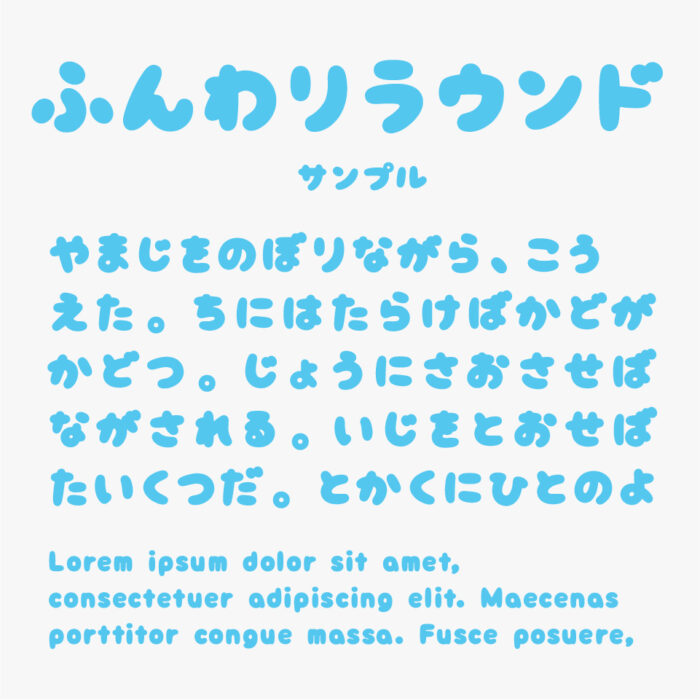
ふんわりラウンド
ふんわりラウンドフォント
ふんわりラウンドフォントは、やや手描き風の骨格で、丸ゴシックのような太めの先端丸の線のベースとしている手書き風フォントです。
ふわふわな雲のような丸みがあり可愛らしいフォントになっているので、子供っぽいデザインとの相性が良いフォントです。
ふんわりラウンド
収録文字は、ひらがな、カタカナ、数字、アルファベット、記号の一部が入っています。漢字は入ってません。(※スペースを除き全435文字)